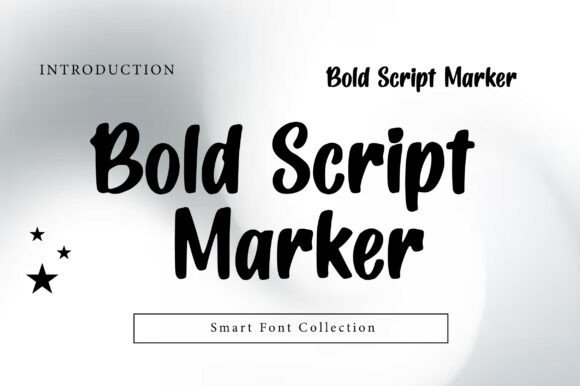
Bold Script Marker
หากคุณกำลังมองหาเนื้อหาคุณภาพสูงเช่น Bold Script Marker แพ็คเกจพรีเมียมนี้เป็นตัวเลือกที่ยอดเยี่ยมสำหรับโปรเจ็กต์สร้างสรรค์ของคุณ
ไม่ว่าคุณจะสร้างผลิตภัณฑ์ POD (Print on Demand) คำเชิญงานแต่งงาน หรือกราฟิกโซเชียลมีเดีย Bold Script Marker ก็เหมาะสมอย่างยิ่ง